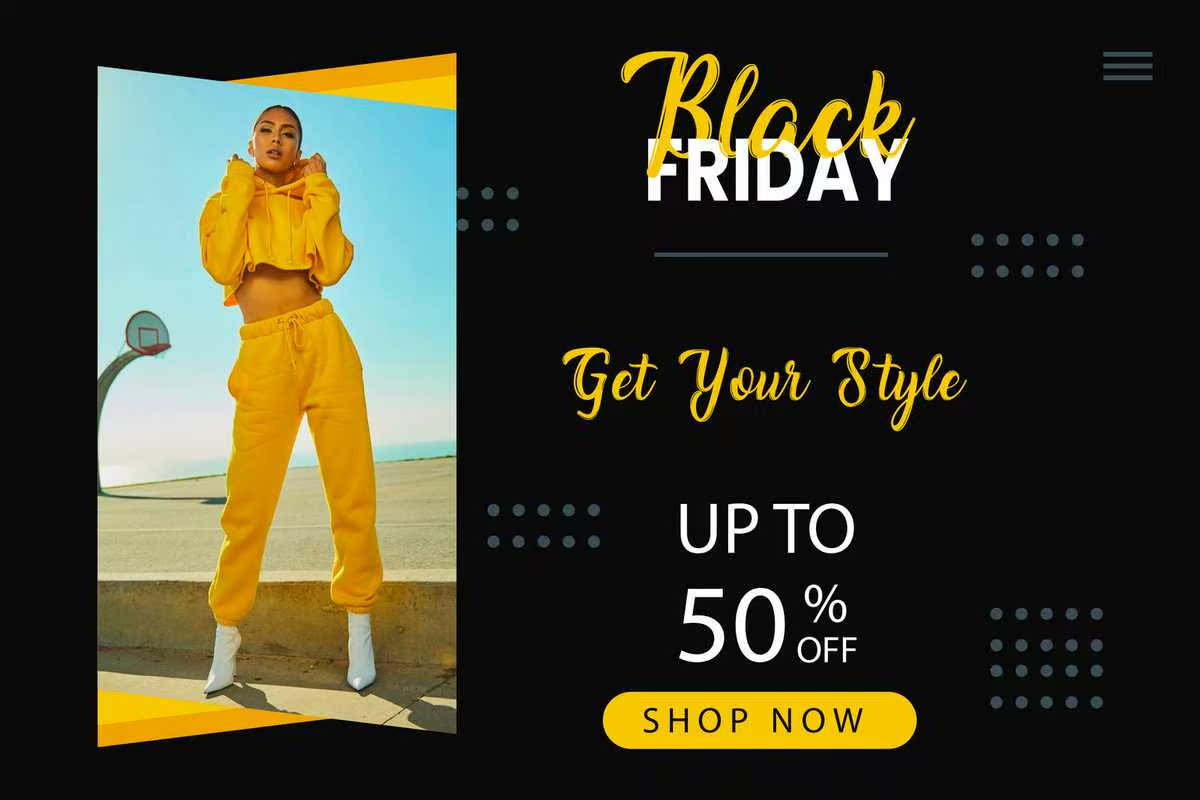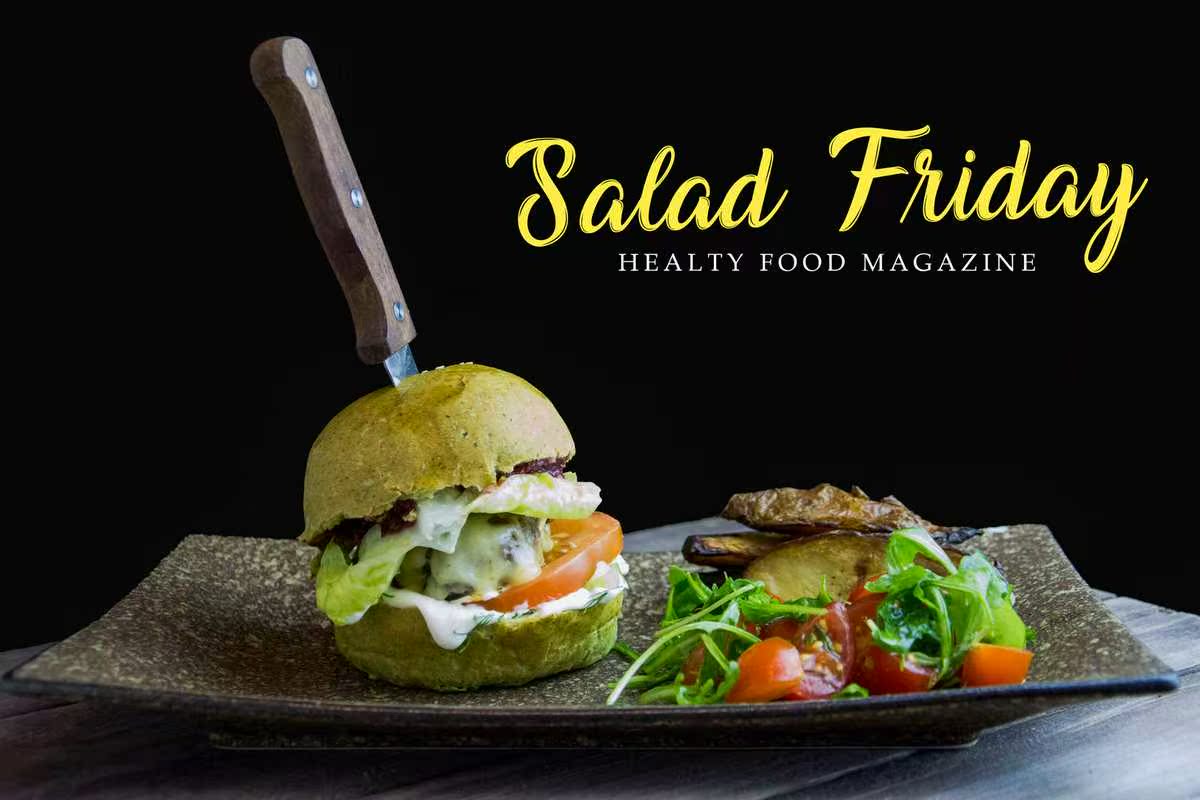
JHOIBOYFONTS是一种任意字体形状变化的随意纹理,可创建一种完美而独特的设计。JHOIBOYFONTS有8个可选项,7个可选项用于小写,1个可选项用于大写,除了适合您的连字和多语言支持外,JHOIBOYFONT是一种随意的粗糙纹理,它可以通过任何字体形状的变化创建一种完美而独特的设计。JHOIBOYFONT有8个可选项,7个可选项用于小写,1个可选项用于大写,以及适合您的连字和多语言支持。